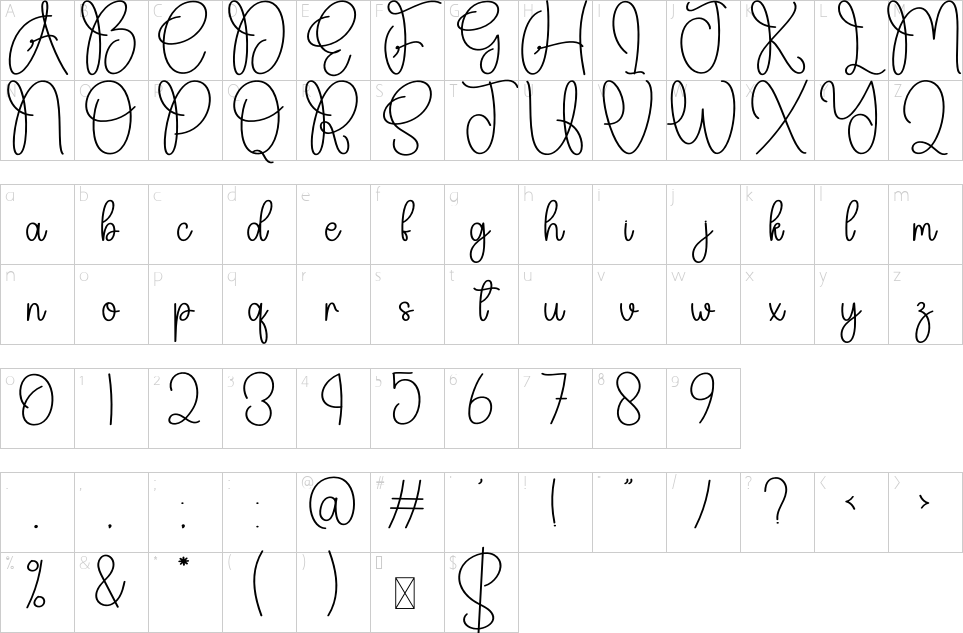
A Angelic font é um recurso gráfico gratuito para Windows e Mac, criado pelo designer scratchones. Com um design delicado e elegante, essa fonte é ideal para projetos que valorizam uma atmosfera suave e harmônica. Ela foi descarregada 550 vezes, evidenciando sua popularidade entre designers e criadores de conteúdo. Se você está procurando por uma fonte que transmita paz e suavidade sem comprometer a legibilidade, a Angelic font pode ser a escolha perfeita. Sua simplicidade e elegância tornam-a uma opção ótima para criações que buscam um estilo mais leve e contemplativo.